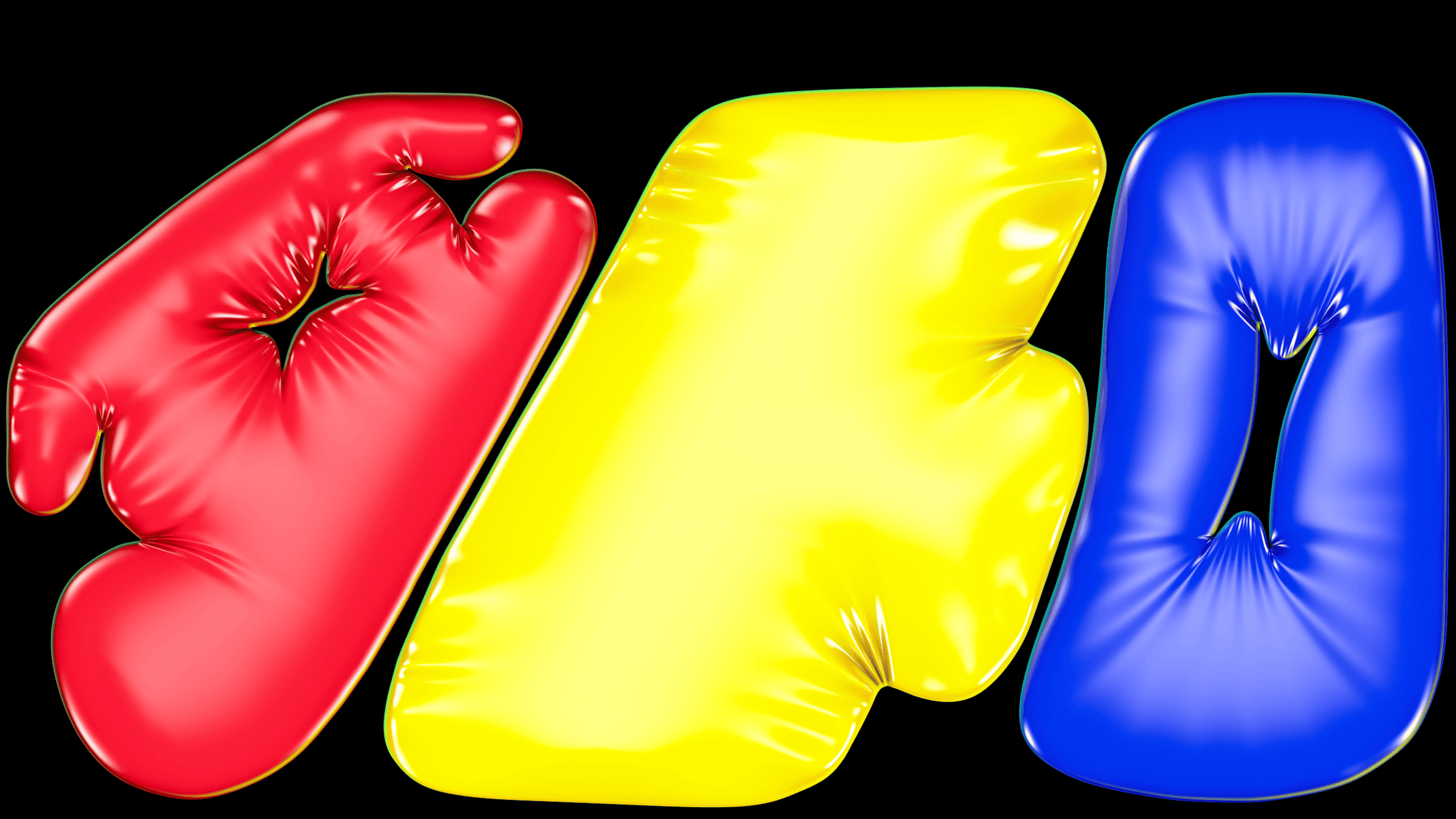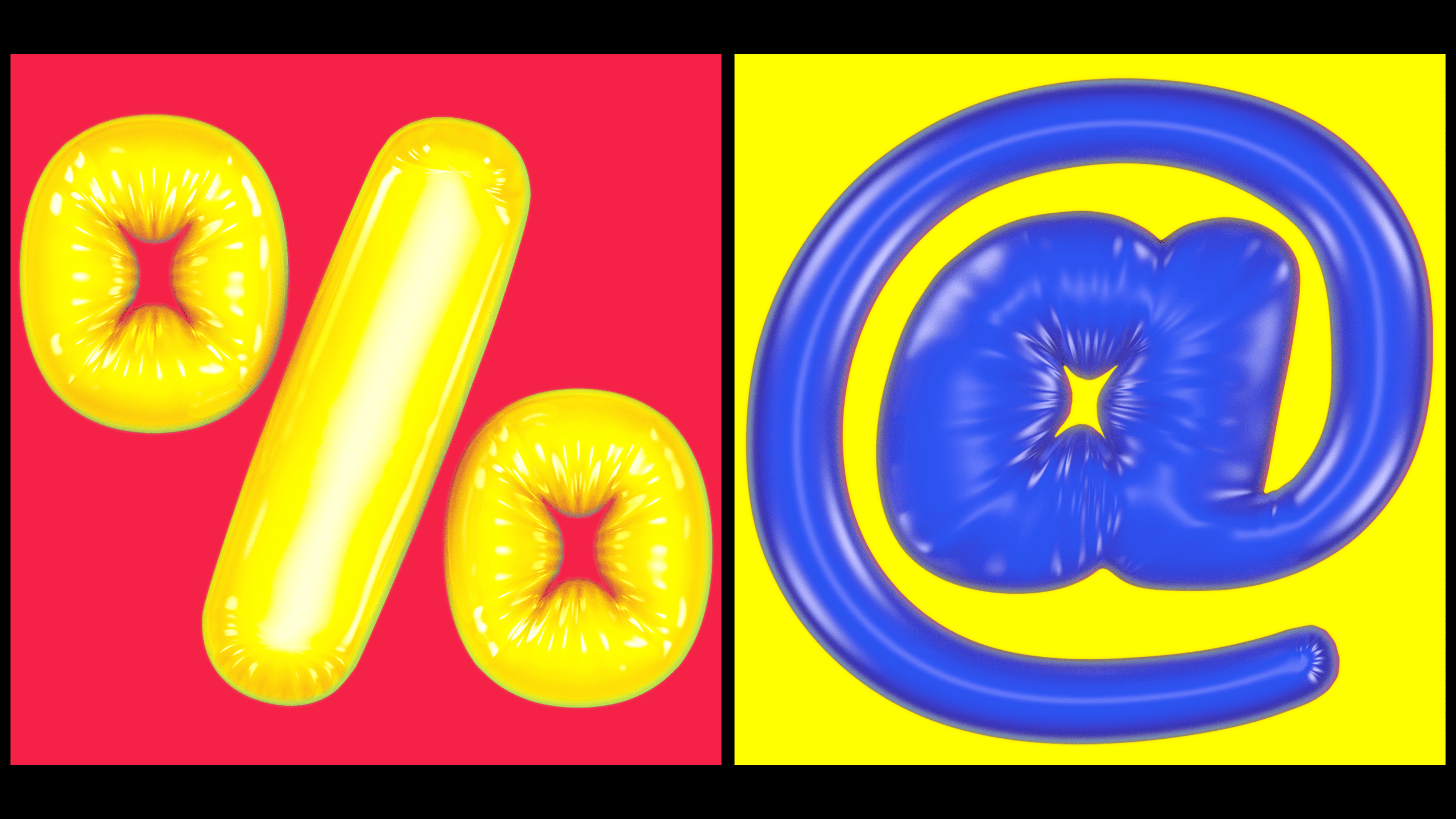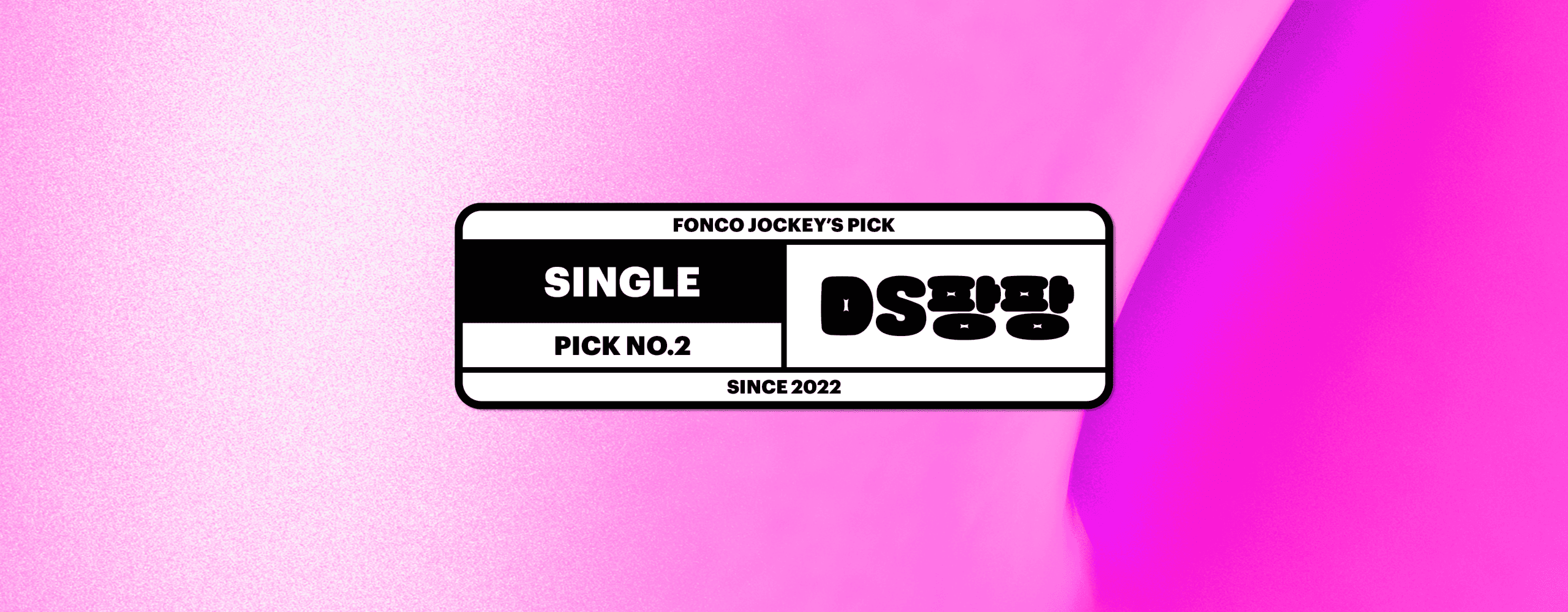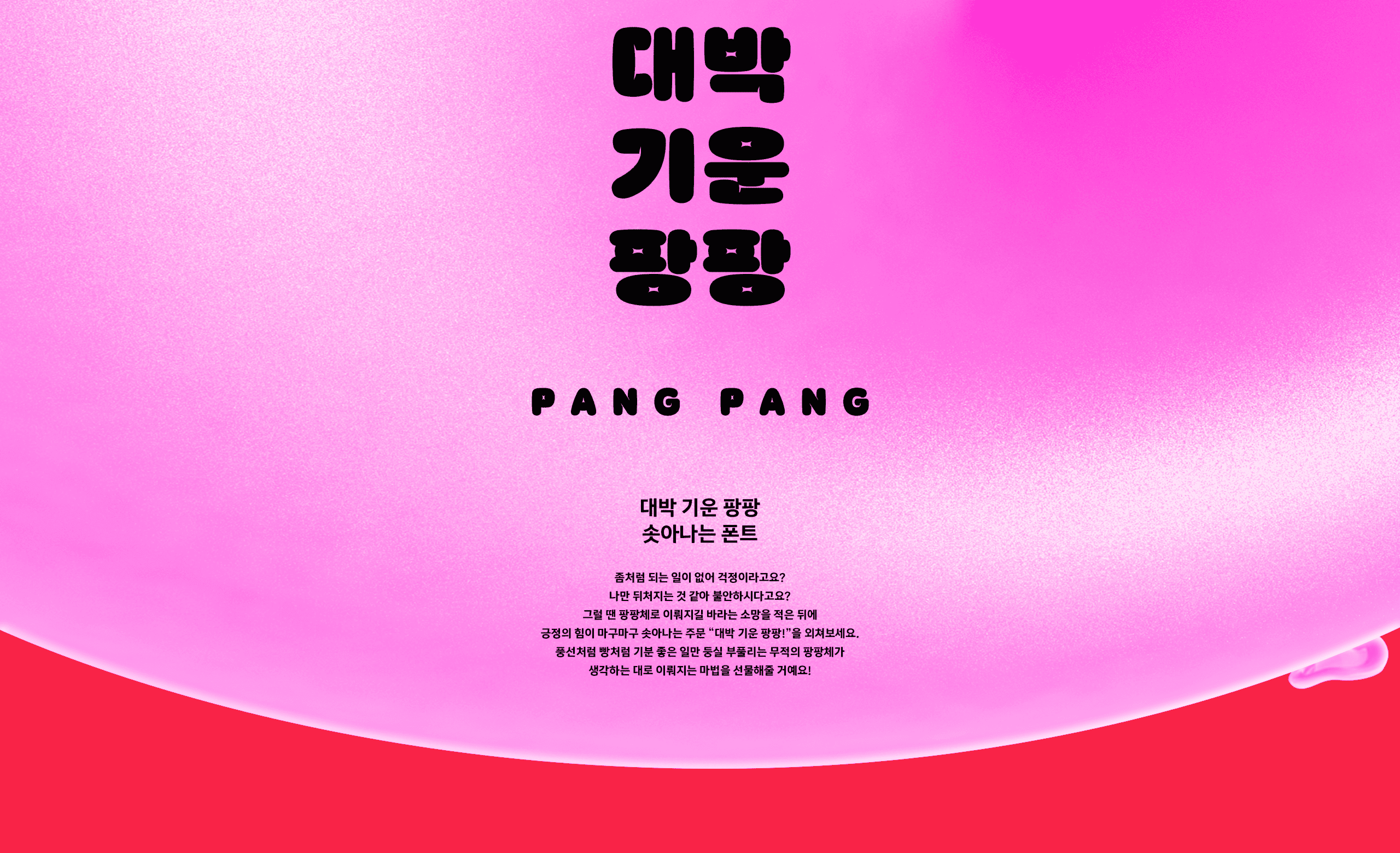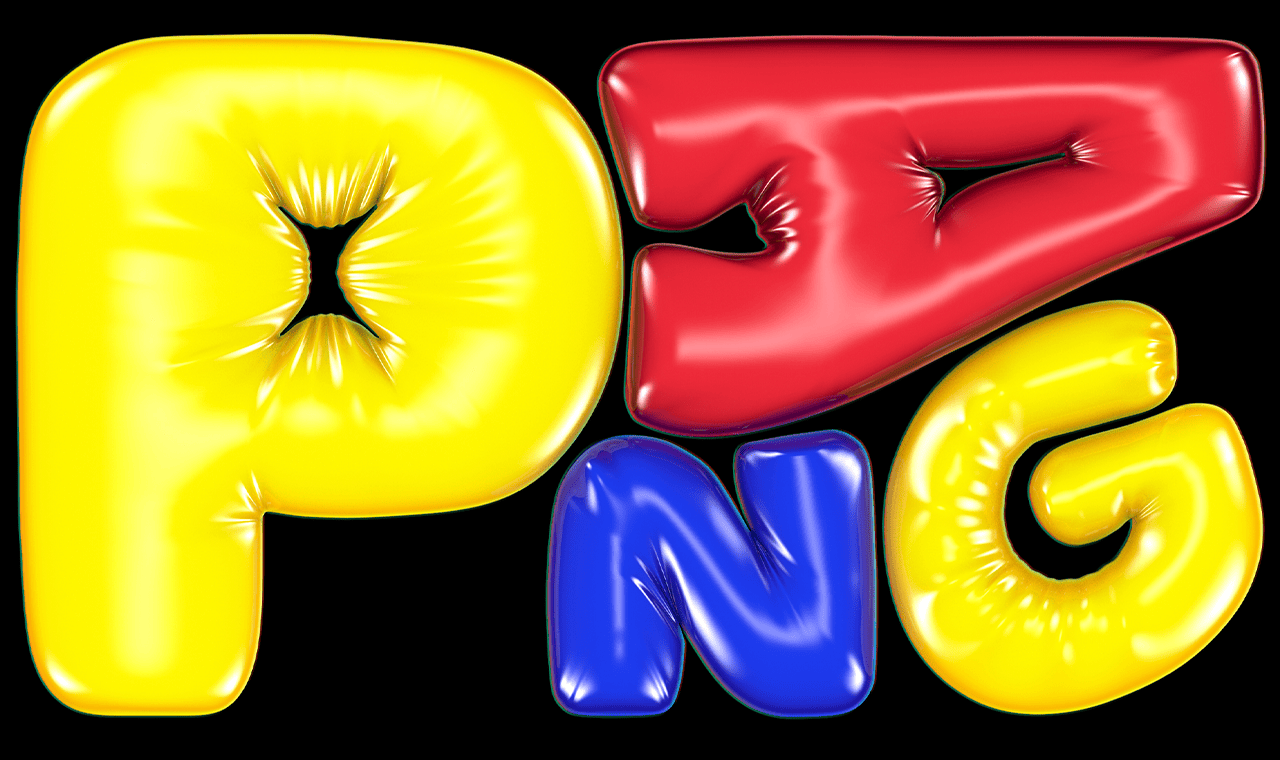
좀처럼 되는 일이 없어 걱정이라고요? 나만 뒤처지는 것 같아 불안하시다고요? 그럴 땐 팡팡체로 이뤄지길 바라는 소망을 적은 뒤에 긍정의 힘이 마구마구 솟아나는 주문 "대박 기운 팡팡!"을 외쳐보세요. 풍선처럼 빵처럼 기분 좋은 일만 둥실 부풀리는 무적의 팡팡체가 생각하는 대로 이뤄지는 마법을 선물해줄 거예요!
제작사
엉뚱상상
제작사 소개
엉뚱상상은 폰트를 뿌리 삼아 엉뚱하고 다채로운 상상력을 펼쳐가는 활기찬 디자인 스튜디오입니다. 우리는 폰트를 읽고 쓰는 글자에 한정하기보다 만지고 감각하는 놀이의 도구로 확장하여 바라봅니다. 그리고 이러한 관점에 따라, 오감을 자극하는 색다른 폰트들을 기획·제작하고 다양한 방식으로 타입 플레이하며 폰트 자체가 하나의 문화를 표상할 방법들을 만들어가고자 합니다.
디자이너
레터빌런 (이상민, 김정진, 김민주, 이병헌)
디자이너 소개
레터빌런은 2021년 결성된 4인조 서체 디자인 그룹으로, 파격적인 한글 디자인을 통해 다음 세대에 타이포그래피에 대한 개념을 고민하고 제안하는 글자를 디자인합니다.